Бесплатные русские шрифты (120 штук)
Доброе время суток, друзья! Давненько я не выкладывал русские шрифты в блоге! Я собирал интересные шрифты, складывал их в папки, убирал с рабочего стола, чтобы как будет время залить их на сайт, но руки никак не доходили! И вот сегодня настал тот день, когда я все таки добрался до них, отобрал русские кириллические шрифты, которые действительно являются именно русскими шрифтами, а не какими-то непонятными символами. Отбирал я в ручную! Сначала залил все шрифты, которые у меня есть на сайте, установил к себе на винду (в который раз открываю для себя прелесть моей же сборки Русские кириллические шрифты — там есть офигенные шрифты, которые мне нравятся). Потом сделал изображения-превью для каждого шрифта, объединил файл ttf с картинкой в архив и залил к себе на сервер.
В данной сборке русских шрифтов представлены только кириллические шрифты с русской раскладкой! Всего здесь представлено 120 шрифтов, некоторые из которых содержат в себе не только классическую раскладку шрифта Regular, но и Bold, Italic, Decor и Bold-Italic. Смотрите, выбирайте, скачивайте, радуйтесь :))
Стильный техно шрифт 20_db
СкачатьДекоративный русский шрифт a_AlgeriusNr
СкачатьСтранный шрифт a_AlternaCmD
СкачатьМягкий русский шрифт a_AlternaSw
СкачатьКириллический шрифт a_AlternaTitulB с полузаливкой
СкачатьКлассический шрифт с засечками a_AntiqueTitulGr
СкачатьСтильный русский шрифт a_AssuanBrk
СкачатьПрозрачный шрифт a_AvanteCpsL без зачечек
СкачатьДекоративный шрифт a_BentTitulDcFr с полоской внизу и наверху
СкачатьЖирный шрифт a_BighausTitul без засечек
СкачатьРисованный русский шрифт a_BighausTitulBrkHil
СкачатьРусский шрифт a_BighausTitulOtlDr с точками
СкачатьЛегко-декоративный шрифт a_BosaNovaCp
СкачатьПриятный кириллический шрифт a_BosaNovaDcFr в стиле римских заголовков
СкачатьРусский шрифт a_BosaNovaOtl с обводкой
СкачатьДекоративный жирный русский шрифт a_BraggaOtl
СкачатьРазновидность предыдущего шрифта с верхней тенью a_BraggaOtlSh
СкачатьДекоративный кирилличекий шрифт a_BraggaStrip
СкачатьНаклонный русский шрифт a_BraggaTitul
СкачатьГалантерейный сдержанный шрифт a_Bremen
СкачатьРусский шрифт a_BremenCaps в стиле русских сказок
СкачатьРазновидность предыдущего шрифта a_BremenCapsNr
СкачатьПредыдущий шрифт, только с полоской внизу и наверху под названием a_BremenDcFr
СкачатьСпортивный русский шрифт a_CampusGrav
СкачатьШрифт в полоску a_CampusMarine
СкачатьКириллический спортивный шрифт a_CampusOtl
СкачатьДекоративный жирный шрифт a_CampusPrLy
СкачатьТот же шрифт, только с тенью a_CampusPrsp
СкачатьРусский шрифт a_CampusStrip в полоску
СкачатьРисованный кириллический шрифт a_ConceptoTit
СкачатьНарисованный шрифт a_ConceptoTitulNrFy
Русский шрифт a_DiscoSerif в кружочек
СкачатьРусский шрифт a_DiscoSerifDbl с двойным кругом во круг букв
СкачатьНаклонный русский шрифт a_Empirial без засечек
СкачатьРусский шрифт a_EmpirialCmDn с фоном
СкачатьРусский шрифт a_GildiaLnBk по типу Вестерн
СкачатьОчень жирный шрифт a_GlobusLnBk
СкачатьНаклонный жирный шрифт a_GlobusOblique
СкачатьТрафаретный жирный русский шрифт a_Groto
СкачатьТрафаретный русский шрифт a_GrotoGr с обводкой
СкачатьДекоративный рисованный шрифт a_LatinoTitulBr
Русский техно шрифт a_LCDNova3DCmObl как на часах
СкачатьРусский шрифт a_LCDNovaObl как на электронных часах
СкачатьКириллический шрифт a_MachinaOrtoDgStr с косыми полосками
СкачатьРусский шрифт без засечек a_MachinaOrtoSht с рисункой паутины
СкачатьДекоративный шрифт юез засечек a_MachinaOrtoSls
СкачатьЕще один шрифт a_ModernoDcFr в стиле древнего Рима
СкачатьПрикольный шрифт a_PlakatTitulHlStr
СкачатьРусский шрифт a_RombyGr, у которого буквы в ромбике с фоном
СкачатьРусский шрифт a_RombyOtl, у которого буквы в ромбике (без фона)
СкачатьИнтересный русский декоративный шрифт a_RombyRndOtl
СкачатьКлассический шрифт a_SeriferTitul с засечками
СкачатьСпорт шрифт a_Simpler2Otl с обводкой
СкачатьКреативный русский шрифт a_SimplerBrk
СкачатьПриятный прозрачный шрифт с обводкой a_SimplerClg
СкачатьИграющий русский шрифт a_SimplerFnt
СкачатьЕще один вид спорт шрифта a_SimplerGr
СкачатьКлассный креативный русский шрифт a_StamperBrk
СкачатьКлассический шрифт AleksandraC с элементами декора
СкачатьТрафаретный шрифт без засечек Archive
СкачатьКлассический русский шрифт без засечек Arsenal
СкачатьРукописный кириллический шрифт BadScript
СкачатьЖирный шрифт без засечек BananaBrick
СкачатьРукописный русский шрифт BetinaScriptCTT
СкачатьПредыдущий шрифт, только пожирнее BetinaScriptExtraCTT
СкачатьПрикольный жирный шрифт Brava
Русский шрифт без засечек Casper
СкачатьСтильный простой шрифт Comfortaa
СкачатьТонкий русский шрифт Cony
СкачатьРусский кириллический шрифт Cuprum
СкачатьЖирный декоративный шрифт Dan
СкачатьОчень классный шрифт Days (напоминает жирный calibri)
СкачатьКлассический шрифт без засечек Eurofurence
СкачатьРукописный наклонный шрифт Flow
СкачатьШрифт с тенью FuturisShadowC без засечек
СкачатьПриятный русский шрифт GardensC
СкачатьКириллический шрифт с прямыми засечками HaginCapsMedium
СкачатьПростой жирынй шрифт Intro
СкачатьРусский шрифт Ivan
СкачатьРусский шрифт IzhitsaC из русских сказок
СкачатьРукописный шрифт JakobCTT
СкачатьРусский рукописный шрифт Jikharev
СкачатьКириллический шрифт Kaori с шумом
СкачатьНебрежно- отрисованный шрифт London
СкачатьШрифт из русских сказок Megen
СкачатьТолстый шрифт с маленькими прямыми засечками Metro
СкачатьОчень толстый шрифт Mod
СкачатьВытянутый русский шрифт Montblanc
СкачатьПриятный русский шрифт для заголовков Movavi
СкачатьИзвестный шрифт Neucha в русской раскладке
СкачатьТрафретный тезно шрифт New_Zelek
СкачатьКлассный русский шрифт Pacifica
СкачатьДекоратвный шрифт PaladinPCRus в стиле заголовков из русских сказок
СкачатьПростой русский шрифт с небольшими засечками Philosopher
СкачатьКлассический шрифт без засечек Play
СкачатьРусский шрифт PTSans
СкачатьРазновидно последнего шрифта PTSansCaption
СкачатьНебезызвестный шрифт PTSerif в кириллической раскладке
СкачатьКлассический шифрт Scada
СкачатьРаспространенный в Европе шрифт SegoeWP
СкачатьРусский шрифт, стилизованный под японские иероглифы SheruPro
СкачатьДекоративный старославянский шрифт Slavjanic
Настоящий спортивный русский шрифт SportsWorld
СкачатьСтильынй кириллический шрифт Sreda
СкачатьДекоративный шрифт SS_Adec_initials
СкачатьКлассный шрифт SS_Adec_main
СкачатьРазновидность прошлого шрифта под названием SS_Adec_text
СкачатьРукописный декоративный шрифт TkachenkSketch
СкачатьСтарорусский шрифт Torhok
СкачатьКлассический рукописный шрифт UkrainianDecor
СкачатьНаклонный русский шрифт с прямыми засечками XeniaWesternC
СкачатьПростой рукописный шрифт Zapf-ChanceC
СкачатьВеселый мультяшный шрифт ITCBeeskneesCyrillic
Скачать
Сборка получилась большой, но я не стал разбивать на две статьи. Также вы можете тут скачать русские шрифты. А также все эти 120 шрифтов вы можете скачать одним архивом тут↓
bayguzin.ru
Русские кириллические шрифты
100% русские кириллические шрифты в размере 70 штук (уже не 70, я решил добавлять сюда новые и новые шрифты). Все шрифты проверены мной и являются именно русскими. Здесь вы найдете и декоративные и стилизованные под какую-то тему и просто красивые русские кириллические шрифты. Сколько раз в интернете я искал русские шрифты, но постоянно натыкался на не честные сборки под названием Кириллические русские шрифты. Я скачивал, распаковывал, устанавливал, но именно русских шрифтов я там не замечал или замечал, но маленькую часть. Будучи уже создав этот блок я решил, что буду делать только качественный сборки, которые действительно имеют рабочие варианты, в данном случае, шрифтов. Здесь вы найдете и обычные классически русские шрифты, готические, декоративные, техно шрифты и так далее. Кстати многие ищут Кириллические шрифты, но это не означает, что в них будет русская версия этого шрифта.
В кириллицу входят 8 языков, 8 шрифтов. У меня же в этой сборке и в остальных под названием Русские кириллические шрифты во всех кириллических шрифтах есть русский язык. Единственный минус: многие шрифты у меня без вариаций bold, italic и так далее. Но если постараться Вы можете найти тот или иной шрифт, если он Вам приглянулся, в интернете. Вы наверняка найдете версию с жирным, курсивном и т.д. вариантами.
В основном русский шрифт требуется web-дизайнеру не для windows или mac, а для Photoshop. Все эти шрифты работаю нормально во всех версиях фотошопа. Если кто не знает, объясняю как установить тот или иной шрифт на windows и собственно пользоваться им в Adobe Photoshop. Это делается очень просто, скачиваете понравившийся шрифт, распаковываете его, кликаете на сам файл шрифта и там будет кнопка установить, жмете ее и все)) Шрифт установлен. Обычно все шрифты лежат вот в такой директории C:\Windows\Fonts. Дальше открываете фотошоп и выбираете в списке шрифтов нужный вам шрифт и пишите на нем русскую речь)) Ну а вот и сами шрифты:
Интересный русский кириллический шрифт Ograda
СкачатьЗвериный русский шрифт LC Bagira
СкачатьДекоративный русский шрифт Xorx_windy Cyr
СкачатьРусский шрифт как на долларовой банкноте Dollar
СкачатьКириллический русский шрифт, написанный от руки Lazy
СкачатьСтильный вытянутый русский шрифт Clip
СкачатьДекоративный рунический русский шрифт Runic
СкачатьИнтересный кириллический русский шрифт Zipper
СкачатьРусский шрифт Moon из мультика Незнайка на луне
СкачатьРусский кириллический шрифт марки автомобиля Porsche
СкачатьРусский шрифт с эффектом ветра Whirl
СкачатьПрописной декоративный русский шрифт Viva
СкачатьКрасивый кириллический русский шрифт Saffron
Красивый кириллический русский шрифт Joke
СкачатьОчень красивый декоративный русский шрифт Decor
СкачатьВампирский кириллический шрифт Algerius
СкачатьРусский шрифт только для заглавных букв Inset
СкачатьЖирный кириллический шрифт с обводкой A_brag
СкачатьКрасивый русский шрифт для граффити Graffty
СкачатьКреативный русский шрифт с засечками Butter
СкачатьНебрежный стильный кириллический шрифт Floyd
СкачатьЖирный кириллический техно-шрифт Aksent
СкачатьКрасивый прописной кириллический шрифт Astra
СкачатьПростой русский прозрачный шрифт futur
СкачатьРусский шрифт, выполненный в стиле Военный трафарет
СкачатьПросто прозрачный шрифт RodchenkoInlineC
СкачатьОчень красивый декоративный русский шрифт Fontocide
СкачатьГотический русский шрифт Ogilvie Cyr
СкачатьПрикольный рисованный русский шрифт DS Down Cyr
СкачатьКириллический русский шрифт DS Eraser Cyr
СкачатьБесплатный русский шрифт TauernCTT
СкачатьБесплатный кириллический шрифт с шумом MatterhornCTT
СкачатьРастянутый русский шрифт с эффектом ветра Slipstream
СкачатьКрасивый рисованный кириллический шрифт palette
СкачатьКреативный русский шрифт в стиле игры Packman
СкачатьРусский кириллический шрифт с тенью a_CampusOtl3DShad
СкачатьКачественный русский шрифт EpsilonCTT
СкачатьЗимний русский шрифт со снегом на буквах Zanesennyj
СкачатьКреативный кириллический шрифт Kashmir
СкачатьКолючий русский шрифт a_ModernoBrk
СкачатьКрасивый жирный техно шрифт на русском языке Ben Pioneer
СкачатьОчень красивый рисованный русский шрифт ds_brushes
СкачатьОчень красивый прописной русский шрифт LegendeC_Plain
СкачатьТочечный русский шрифт FDMedian для вывесок
СкачатьСтильный рисованный кириллический шрифт Bonzai
СкачатьАккуратный кириллический русский шрифт ISOCTEUR
СкачатьДекоративный очень красивый русский шрифт Bickham Script Two
СкачатьКрасивый кириллический шрифт со звездами moonlight
СкачатьСтаринный декоративный русский шрифт Sevilla Decor
СкачатьОчень красивый кириллический шрифт Art Nouveau-Bistro
СкачатьГотический кириллический шрифт Arthur Gothic
СкачатьКреативный русский шрифт в форме спирали BM spiral Cap Cyr
СкачатьКрасивый декоративный кириллический шрифт Wooden Ship Decorated
СкачатьАккуратный готический русский шрифт Agatha-Modern
СкачатьПрописной русский шрифт Scrawl, написанный от руки
СкачатьГотический русский шрифт PaladinRus, в стиле средневековой Европы
СкачатьГотический кириллический русский шрифт Advokat Modern
СкачатьКрасивый русский шрифт Tusch Touch 3, написанный от руки
СкачатьРукописный кириллический шрифт Acquest Script
СкачатьАккуратный рукописный русский шрифт Adine Kirnberg
СкачатьЕще один русский рукописный шрифт Alexandra_Script
СкачатьСтильный рисованный кириллический шрифт LC Blowzy
СкачатьКрасивый русский кириллический шрифт MinusmanC
СкачатьЭлегантный русский рукописный шрифт Alexandra Zeferino One
СкачатьСтрогий декоративный русский шрифт Elzevir
СкачатьДекоративный русский шрифт в стиле 18 века Ekaterina Velikaya Two
СкачатьМультипликационный русский шрифт Disney Park
СкачатьБольшой жирный кириллический шрифт LATIN
СкачатьКлассический кириллический русский шрифт Bickham Script One
СкачатьГотический кириллический шрифт GothicRus
СкачатьПростой классический русский шрифт Prosto
СкачатьСтильный шрифт Ubuntu с кириллической раскладкой
Скачать
Красивый шрифт Underdog в кириллической раскладке
Скачать
Все эти шрифты одним архивом вы можете скачать, нажав на кнопку Скачать, а также можете скачать все шрифты, которые я выкладывал за все время вот в этой сборке
bayguzin.ru
Веселые мультяшные шрифты в количестве 15 штук
Здравствуйте, дорогие друзья. Давненько я не выкладывал шрифты, которые пользовались большой популярностью у меня сайте. И тут столкнулся с поиском мультяшного шрифта для одного лого и решил сделать сборку из 15-и веселых мультяшных кириллических шрифтов. Некоторые шрифты из этой сборки встречаются в предыдущих моих постах, но я все равно выложил, чтобы было из чего выбрать. Тут есть шрифт из Disney, Ледникового периода, Незнайки на Луне. Каждый шрифт вы сможете скачать отдельно прямо с моего сервера без помощи каких-либо файлообменников и, самое главное, совершенно бесплатно. Поехали:
Рисованный мультяшный кириллический шрифт
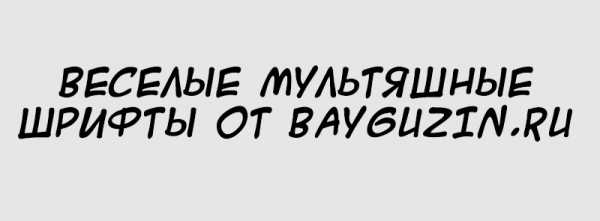
Классный веселый русский шрифт
Кириллический шрифт Disney
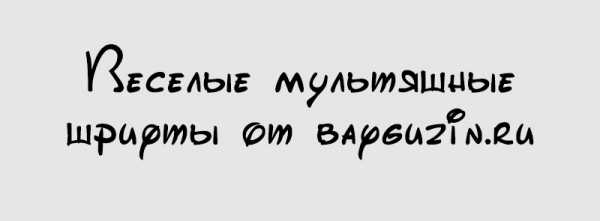
Жирный кириллический шрифт из мультика
Стильный рисованный мультяшный шрифт
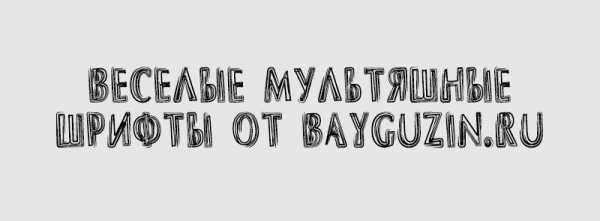
Веселый жирный шрифт для титров мультика
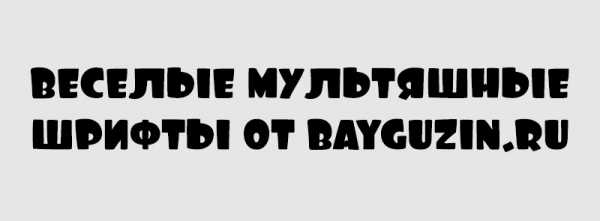
Контурный мультяшный русский шрифт
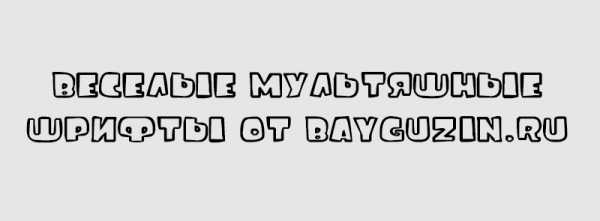
Классный веселый кириллический шрифт
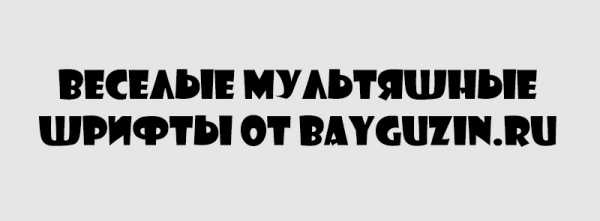
Контурный моноширинный мультяшный шрифт
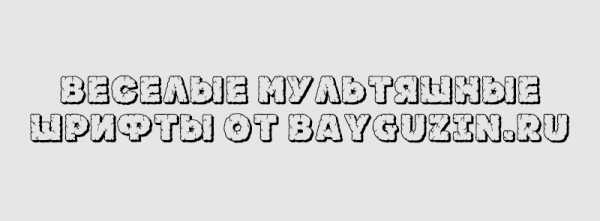
Моноширинный мультяшный кириллический шрифт
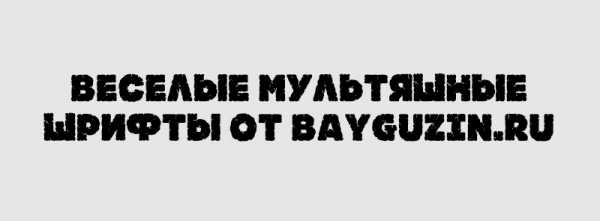
Шрифт для титров в мультике
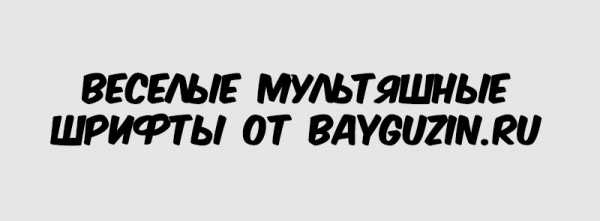
«Безалаберный» мультяшный кириллический шрифт
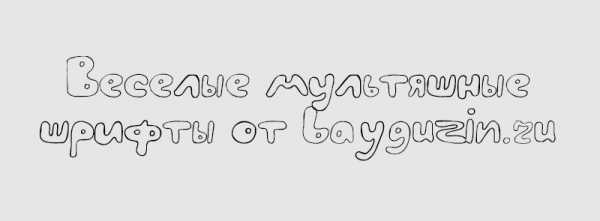
Русский шрифт из «Незнайка на луне»
Строгий, но веселый шрифт в кириллической раскладке
Тонкий мультяшный шрифт
Вот все 15 кириллических шрифтов из этой сборки, которые можно использовать для титров мультика или веселого фильма, для создания веселого яркого логотипа, баннера на детскую тематику. Хорошая сборка получалась, качайте. Кстати все 15 шрифтов вы можете скачать по ссылке ниже.
bayguzin.ru
Бесплатные русские шрифты (120 штук)
Доброе время суток, друзья! Давненько я не выкладывал русские шрифты в блоге! Я собирал интересные шрифты, складывал их в папки, убирал с рабочего стола, чтобы как будет время залить их на сайт, но руки никак не доходили! И вот сегодня настал тот день, когда я все таки добрался до них, отобрал русские кириллические шрифты, которые действительно являются именно русскими шрифтами, а не какими-то непонятными символами. Отбирал я в ручную! Сначала залил все шрифты, которые у меня есть на сайте, установил к себе на винду (в который раз открываю для себя прелесть моей же сборки Русские кириллические шрифты — там есть офигенные шрифты, которые мне нравятся). Потом сделал изображения-превью для каждого шрифта, объединил файл ttf с картинкой в архив и залил к себе на сервер.
В данной сборке русских шрифтов представлены только кириллические шрифты с русской раскладкой! Всего здесь представлено 120 шрифтов, некоторые из которых содержат в себе не только классическую раскладку шрифта Regular, но и Bold, Italic, Decor и Bold-Italic. Смотрите, выбирайте, скачивайте, радуйтесь :))
Стильный техно шрифт 20_db
СкачатьДекоративный русский шрифт a_AlgeriusNr
СкачатьСтранный шрифт a_AlternaCmD
СкачатьМягкий русский шрифт a_AlternaSw
СкачатьКириллический шрифт a_AlternaTitulB с полузаливкой
СкачатьКлассический шрифт с засечками a_AntiqueTitulGr
СкачатьСтильный русский шрифт a_AssuanBrk
СкачатьПрозрачный шрифт a_AvanteCpsL без зачечек
СкачатьДекоративный шрифт a_BentTitulDcFr с полоской внизу и наверху
СкачатьЖирный шрифт a_BighausTitul без засечек
СкачатьРисованный русский шрифт a_BighausTitulBrkHil
СкачатьРусский шрифт a_BighausTitulOtlDr с точками
СкачатьЛегко-декоративный шрифт a_BosaNovaCp
СкачатьПриятный кириллический шрифт a_BosaNovaDcFr в стиле римских заголовков
СкачатьРусский шрифт a_BosaNovaOtl с обводкой
СкачатьДекоративный жирный русский шрифт a_BraggaOtl
СкачатьРазновидность предыдущего шрифта с верхней тенью a_BraggaOtlSh
СкачатьДекоративный кирилличекий шрифт a_BraggaStrip
СкачатьНаклонный русский шрифт a_BraggaTitul
СкачатьГалантерейный сдержанный шрифт a_Bremen
СкачатьРусский шрифт a_BremenCaps в стиле русских сказок
СкачатьРазновидность предыдущего шрифта a_BremenCapsNr
СкачатьПредыдущий шрифт, только с полоской внизу и наверху под названием a_BremenDcFr
СкачатьСпортивный русский шрифт a_CampusGrav
СкачатьШрифт в полоску a_CampusMarine
СкачатьКириллический спортивный шрифт a_CampusOtl
СкачатьДекоративный жирный шрифт a_CampusPrLy
СкачатьТот же шрифт, только с тенью a_CampusPrsp
СкачатьРусский шрифт a_CampusStrip в полоску
СкачатьРисованный кириллический шрифт a_ConceptoTit
СкачатьНарисованный шрифт a_ConceptoTitulNrFy
СкачатьРусский шрифт a_DiscoSerif в кружочек
СкачатьРусский шрифт a_DiscoSerifDbl с двойным кругом во круг букв
СкачатьНаклонный русский шрифт a_Empirial без засечек
СкачатьРусский шрифт a_EmpirialCmDn с фоном
СкачатьРусский шрифт a_GildiaLnBk по типу Вестерн
СкачатьОчень жирный шрифт a_GlobusLnBk
СкачатьНаклонный жирный шрифт a_GlobusOblique
СкачатьТрафаретный жирный русский шрифт a_Groto
СкачатьТрафаретный русский шрифт a_GrotoGr с обводкой
СкачатьДекоративный рисованный шрифт a_LatinoTitulBr
Скачать
Русский техно шрифт a_LCDNova3DCmObl как на часах
СкачатьРусский шрифт a_LCDNovaObl как на электронных часах
СкачатьКириллический шрифт a_MachinaOrtoDgStr с косыми полосками
СкачатьРусский шрифт без засечек a_MachinaOrtoSht с рисункой паутины
СкачатьДекоративный шрифт юез засечек a_MachinaOrtoSls
СкачатьЕще один шрифт a_ModernoDcFr в стиле древнего Рима
СкачатьПрикольный шрифт a_PlakatTitulHlStr
СкачатьРусский шрифт a_RombyGr, у которого буквы в ромбике с фоном
СкачатьРусский шрифт a_RombyOtl, у которого буквы в ромбике (без фона)
СкачатьИнтересный русский декоративный шрифт a_RombyRndOtl
СкачатьКлассический шрифт a_SeriferTitul с засечками
СкачатьСпорт шрифт a_Simpler2Otl с обводкой
СкачатьКреативный русский шрифт a_SimplerBrk
СкачатьПриятный прозрачный шрифт с обводкой a_SimplerClg
СкачатьИграющий русский шрифт a_SimplerFnt
СкачатьЕще один вид спорт шрифта a_SimplerGr
СкачатьКлассный креативный русский шрифт a_StamperBrk
СкачатьКлассический шрифт AleksandraC с элементами декора
СкачатьТрафаретный шрифт без засечек Archive
СкачатьКлассический русский шрифт без засечек Arsenal
СкачатьРукописный кириллический шрифт BadScript
СкачатьЖирный шрифт без засечек BananaBrick
СкачатьРукописный русский шрифт BetinaScriptCTT
СкачатьПредыдущий шрифт, только пожирнее BetinaScriptExtraCTT
СкачатьПрикольный жирный шрифт Brava
СкачатьРусский шрифт без засечек Casper
СкачатьСтильный простой шрифт Comfortaa
СкачатьТонкий русский шрифт Cony
СкачатьРусский кириллический шрифт Cuprum
СкачатьЖирный декоративный шрифт Dan
СкачатьОчень классный шрифт Days (напоминает жирный calibri)
СкачатьКлассический шрифт без засечек Eurofurence
СкачатьРукописный наклонный шрифт Flow
СкачатьШрифт с тенью FuturisShadowC без засечек
СкачатьПриятный русский шрифт GardensC
СкачатьКириллический шрифт с прямыми засечками HaginCapsMedium
СкачатьПростой жирынй шрифт Intro
СкачатьРусский шрифт Ivan
СкачатьРусский шрифт IzhitsaC из русских сказок
СкачатьРукописный шрифт JakobCTT
СкачатьРусский рукописный шрифт Jikharev
СкачатьКириллический шрифт Kaori с шумом
СкачатьНебрежно- отрисованный шрифт London
СкачатьШрифт из русских сказок Megen
СкачатьТолстый шрифт с маленькими прямыми засечками Metro
СкачатьОчень толстый шрифт Mod
СкачатьВытянутый русский шрифт Montblanc
СкачатьПриятный русский шрифт для заголовков Movavi
СкачатьИзвестный шрифт Neucha в русской раскладке
СкачатьТрафретный тезно шрифт New_Zelek
СкачатьКлассный русский шрифт Pacifica
СкачатьДекоратвный шрифт PaladinPCRus в стиле заголовков из русских сказок
СкачатьПростой русский шрифт с небольшими засечками Philosopher
СкачатьКлассический шрифт без засечек Play
СкачатьРусский шрифт PTSans
СкачатьРазновидно последнего шрифта PTSansCaption
СкачатьНебезызвестный шрифт PTSerif в кириллической раскладке
СкачатьКлассический шифрт Scada
СкачатьРаспространенный в Европе шрифт SegoeWP
СкачатьРусский шрифт, стилизованный под японские иероглифы SheruPro
СкачатьДекоративный старославянский шрифт Slavjanic
СкачатьНастоящий спортивный русский шрифт SportsWorld
СкачатьСтильынй кириллический шрифт Sreda
СкачатьДекоративный шрифт SS_Adec_initials
СкачатьКлассный шрифт SS_Adec_main
СкачатьРазновидность прошлого шрифта под названием SS_Adec_text
СкачатьРукописный декоративный шрифт TkachenkSketch
СкачатьСтарорусский шрифт Torhok
СкачатьКлассический рукописный шрифт UkrainianDecor
СкачатьНаклонный русский шрифт с прямыми засечками XeniaWesternC
СкачатьПростой рукописный шрифт Zapf-ChanceC
СкачатьВеселый мультяшный шрифт ITCBeeskneesCyrillic
Скачать
Сборка получилась большой, но я не стал разбивать на две статьи. Также вы можете тут скачать русские шрифты. А также все эти 120 шрифтов вы можете скачать одним архивом тут↓
bayguzin.ru
165 русских кириллических шрифтов
Добро. Наконец-то я доделал очередную сборку шрифтов. И она получилась самая большая на моем сайте. В сборке — 165 кириллических шрифтов с русской раскладкой. Пока не забыл сказать: в каждом шрифте имеется как русская раскладка, так и английская. Просто в прошлых сборках шрифтов я помню, что я проверял шрифт на фразе «Блог Эрика Байгузина», а там нет английских букв и из-за этого попадались шрифты, в которых нет английский раскладки.
Как обычно я выкладываю каждый шрифт отдельно, с превью-изображением и отдельной кнопкой для скачки. Правда сейчас я не запаковывал каждый шрифт в архив (зачем я вообще это делал?) и при нажатии на «Скачать» к Вам на компьютер уходит сразу шрифт .ttf (в некоторых случаях .otf).
Каждый шрифт я проверял лично, так что гарантирую работоспособность каждого шрифта, который в этой сборке.
В мыслях есть создать в разделе «Шрифты» не ленту статей и сборок, а вывод ленты шрифтов, чтобы можно было идти по ленте, находить нужный шрифт с помощью фильтра «С засечками, без засечек, старинные, декоративные и так далее». Но над этим нужно поработать, а так мало времени. Вру, лень 🙂 Но я обязательно это сделаю. А пока, смотрите, скачивайте, пользуйтесь. Некоторые шрифты повторяются с другими сборками, но их максимум штук 10-15. Внизу статьи можно скачать все шрифты из этой сборки одним архивом, хотя я предпочитаю не засорять операционную систему и Photoshop не нужными шрифтами, а качать только те, которые понравились.
Декоративный русский шрифт Acquest Script
СкачатьНаклонный декоративный русский Adine Kirnberg
СкачатьМодернисткий русский шрифт Agatha Modern
СкачатьКлассический декоративный шрифт Alexandra Script
СкачатьРусский декор-шрифт Allegretto Script Two
СкачатьШрифт Andantino script в русской раскладке
СкачатьКрасивый декоративный шрифт Angelica
СкачатьАрабский шрифт DS Arabic в русской раскладке
СкачатьШрифт Ariadna script с ярко выраженными заглавными
СкачатьРусский шрифт Arkhive, сделанный под старину
СкачатьАрт-шрифт ArtScript в русской раскладке
СкачатьЖирный декоратинвый шрифт Asessor
СкачатьКириллический наклонный шрифт Astra
СкачатьЕще один декоративный шрифт Aurora script
СкачатьШрифт Bickham Script One в кириллице
СкачатьВариация шрифта Bickham Script Three
СкачатьВариация шрифта Bickham Script Two
СкачатьКириллический шрифт Bolero script
СкачатьТолстый русский шрифт Boyarsky
СкачатьКаллиграфический русский шрифт Caligraph
СкачатьДекоративный русский шрифт Calligraphia One
СкачатьДекоративный русский шрифт Calligraphia Two
СкачатьАккуратный декоративный шрифт Cansellarist
СкачатьСтильный декор-шрифт Carolina
СкачатьДекоративный русский шрифт Cassandra
СкачатьРусский шрифт Ceremonious One с вензелями
СкачатьРусский шрифт Ceremonious Three с вензелями
СкачатьРусский шрифт Ceremonious Two с вензелями
СкачатьАккуратный каллиграфический шрифтChampignon Script
СкачатьРусский кириллический шрифт KB Chopin Script
СкачатьРусский шрифт Connetable
СкачатьШрифт Copyist с завитушками
СкачатьРукописный Corinthia в русской раскладке
СкачатьЖирный рукописный шрифт Corrida Bold
СкачатьЖирный рукописный шрифт Corrida Cyrillic
СкачатьНаклонный рукописный шрифт Cyrillic Brush
СкачатьСтрогий рукописный шрифт Cyrillic Ribbon
СкачатьРусский шрифт Cyrillic Chancellor
СкачатьКлассический Decor CTT в кириллице
СкачатьРусский неряшливый шрифт Dear Joe
СкачатьРукописный русский шрифт Demian
СкачатьИнтересный русский шрифт DisneyPark
СкачатьСтильный шрифт DomCasual
СкачатьПиксельный русский шрифт Dotf
СкачатьШрифт DrPoDecor с декоративными заглавными
СкачатьТонкий русский шрифт DS Note
СкачатьСимпатичный русский шрифт DS Rabbit Medium
СкачатьСамописный русский шрифт DS Eraser
СкачатьРусский шрифт DS Eraser2
СкачатьШрифт с вензелями Ekaterina Velikaya One
СкачатьШрифт с вензелями Ekaterina Velikaya Two
СкачатьКаллиграфический русский шрифт Elzevir
СкачатьАнглийский шрифт English Script на русском
СкачатьСтильный шрифт Epsilon CTT «от руки»
СкачатьСтильный пиксельный шрифт Epson
СкачатьКрасивый декор-шрифт Esenin Script One
СкачатьКрасивый декор-шрифт Esenin Script Two
СкачатьСимпатичный русский шрифт Favorit
Скачать«Неряшливый» шрифт FlowDian
СкачатьПриятный наклонный шрифт FreeHand
СкачатьСтильный шрифт Freestyle в русской раскладке
СкачатьСтрогий русский шрифт Geisha без засечек
СкачатьРусский жирный шрифт Globus
СкачатьШрифт Grinya в кириллической раскладке
СкачатьДекор шрифт Heather Script One в кириллице
СкачатьДекор шрифт Heather Script Two в кириллице
СкачатьДекор шрифт Heather Script в кириллице
СкачатьШрифт Heinrich Text
СкачатьНаклонный русский шрифт Hogarth Script
СкачатьКурсивный русский шрифт Hortensia
СкачатьЗаглавный шрифт Irina
СкачатьСимпатичный шрифт Isabella Decor
СкачатьСтильный «округлый» шрифт Joke
СкачатьКаллиграфический русский шрифт Karnac One
СкачатьЯпонский шрифт Keetano Gaijin в кириллице
СкачатьШрифт в японском стиле Keetano Katakana
Скачать«Сказочный» шрифт Kuritza
СкачатьСтрогий курсивный шрифт Kursiv C
СкачатьСтильный декоративный шрифт Lainy Day
СкачатьШрифт «от руки» Lazy Crazy
СкачатьКонтурный русский шрифт LC Blowzy
СкачатьШрифт «мелом на доске» LC Chalk
СкачатьСтраныый шрифт LK Construct
СкачатьТочечный русский шрифт LK Embroidery
СкачатьИнтересный шрифт LK Fence
СкачатьКлассический шрифт с засечками LehmannC
СкачатьСтрогий декор-шрифт Liana
СкачатьШрифт Liruss TYGRA для сказок
СкачатьРусский шрифт Ludvig van Bethoveen
СкачатьЖирный шрифт Madera TYGRA
СкачатьТонкий русский декор-шрифт Marianna
СкачатьКреативный шрифт MinusmanC
СкачатьРукописный шрифт Mistral
СкачатьШрифт в стиле модерн Modernist Three
СкачатьШрифт в стиле модерн Moderno One
СкачатьШрифт в стиле модерн Moderno Three
СкачатьШрифт в стиле модерн Moderno Two
СкачатьСовременный шрифт MonoFonto
СкачатьШрифт для вывесок Monte Carlo
Скачать«Лунный» шрифт Moon Child
СкачатьРастянутый декоративный шрифт Nadejda
СкачатьСтрогий русский шрифт Newropol
Скачать«Мохнатый» шрифт Ocean
СкачатьКлассический шрифт Odessa Script Cyr
СкачатьРукописный русский шрифт Olga
СкачатьКреативный шрифт P22 Kilkenny Initial Cap
СкачатьШрифт Palette AV с одними заглавными
СкачатьШрифт Park Avenue Normal в кириллице
СкачатьДекор-шрифт Parsek в кириллической раскладке
СкачатьРусский шрифт из Вестернов Patience
СкачатьШрифт PG_IsadoraCyrPro на русском
СкачатьКлассический Present Script в русской раскладке
СкачатьДекоративный шрифт REM
СкачатьРукописный шрифт RoscherkDL
СкачатьШрифт Rubius в кириллице
СкачатьИнтересный русский шрифт Rublik
СкачатьЗаглавный русский шрифт Saffron_Cyr
СкачатьХаотичный шрифт Scrowl
СкачатьКириллический шрифт Scriptorama
СкачатьКлассический шрифт Segoe Print
СкачатьПриятный русский шрифт Sevilla Decor
Скачать«Острый» шрифт Still Time Cyr
СкачатьКрасивый стильный русский шрифт Stylo Bold
СкачатьНаклонный аккуратный шрифт Tagir CTT
СкачатьТонкий шрифт Technical Di
СкачатьСтильный современный шрифт Ticker Tape
СкачатьКаллиграфический шрифт Torhok Italic
СкачатьРусский шрифт с вензелями Venecia
СкачатьТонкий русский декор-шрифт Venski Sad One
СкачатьТонкий русский декор-шрифт Venski Sad Two
СкачатьГотический русский шрифт Verona Gothic
СкачатьКлассический декоративный шрифт Vesna
СкачатьРусский кириллический шрифт VivaldiD Cl
СкачатьЕдинственный русский шрифт без английской раскладки Vladovskiy
СкачатьСтрогий русский шрифт без засечек Wllamette SF
СкачатьКрасивый декоративный шрифт Wooden Ship Decorated
СкачатьНеобычный шрифт Xorx Toothy
СкачатьДекоративный русский шрифт Zeferino One
СкачатьДекоративный русский шрифт Zeferino Three
СкачатьДекоративный русский шрифт Zeferino Two
Скачатьbayguzin.ru
Здесь Вы найдете кириллические шрифты для photoshop, word и других программ. Большинство шрифтов, кроме русских символов содержат и латинские, а также цифры, знаки препинания, скобки и т.п. | |||||||||||||||||||||||||||||||||||||||||
| |||||||||||||||||||||||||||||||||||||||||
| Страница 1 из 10 | |||||||||||||||||||||||||||||||||||||||||
www.takpro100.net.ua
Кириллические русские шрифты для Windows
Данная сборка содержит только кириллические шрифты. Вы можете скачать русские шрифты с моего сайта абсолютно бесплатно. Каждый шрифт проверен лично мною и я гарантирую, что все шрифты в этой сборке поддерживают русский язык. Этот топик я буду делать следующим образом: название кириллического шрифта, изображение этого шрифта и ссылка на скачку прямо с моего сайта. На картинках все шрифты изображены одним размером — 36 пт в Photoshop для того, чтобы вы знали какие шрифты большемерки, какие маломерки. Смотрим, качаем!
Рукописный русский шрифт DS Note
СкачатьРусский шрифт ChinaCyr на китайский манер
СкачатьГотический кириллический шрифт goth
СкачатьВампирский кириллический шрифт с каплями крови
СкачатьКириллический шрифт в техасском стиле Invest
СкачатьПрописной кириллический шрифт Still time
СкачатьРусский техно шрифт, состоящий из точек
СкачатьБесплатный кириллический шрифт для Photoshop
СкачатьЗомби шрифт кириллица
СкачатьАккуратный кириллический шрифт
СкачатьБесплатный русский шрифт для windows
СкачатьПростой кириллический шрифт, сделанный методом обводки
СкачатьКириллический шрифт в стиле quake
СкачатьПрикольный бесплатный русский шрифт
СкачатьБесплатный русский техно шрифт podd
СкачатьПрописной кириллический славянский шрифт
СкачатьКириллический шрифт как на электронных часах
СкачатьЖирный русский шрифт frankC
СкачатьСтильный русский шрифт в стиле печатной машинки
СкачатьКрупный кириллический шрифт
СкачатьРусский шрифт в стиле восемнадцатого века
СкачатьСтарославянский кириллический шрифт yermak
СкачатьБесплатный русский шрифт davidaC
СкачатьПриятный жирный кириллический шрифт
СкачатьКрасивый русский шрифт DS uncial
СкачатьКлассический кириллический шрифт BedrockC
СкачатьРусский шрифт в стиле старорусского написания Beresta
СкачатьКрасивый кириллический шрифт Beastim
СкачатьСтильный жирный русский шрифт DS stamper
СкачатьОчень красивый кириллический шрифт в арабском стиле DS arabic
СкачатьСтильный кириллический шрифт DS stain
СкачатьКириллический Техно шрифт Terminator (размер 24пт)
СкачатьДекоративный кириллический шрифт Ecmann
СкачатьРусский кириллический шрифт DexterC
СкачатьРусский очень красивый шрифт прописью Birch
Скачать«Горящий» русский кириллический шрифт Blaze
СкачатьКреативный прописной русский шрифт Burlak
СкачатьКалиграфический русский шрифт Calligraph
СкачатьИнтересный кириллический шрифт DS eraser2